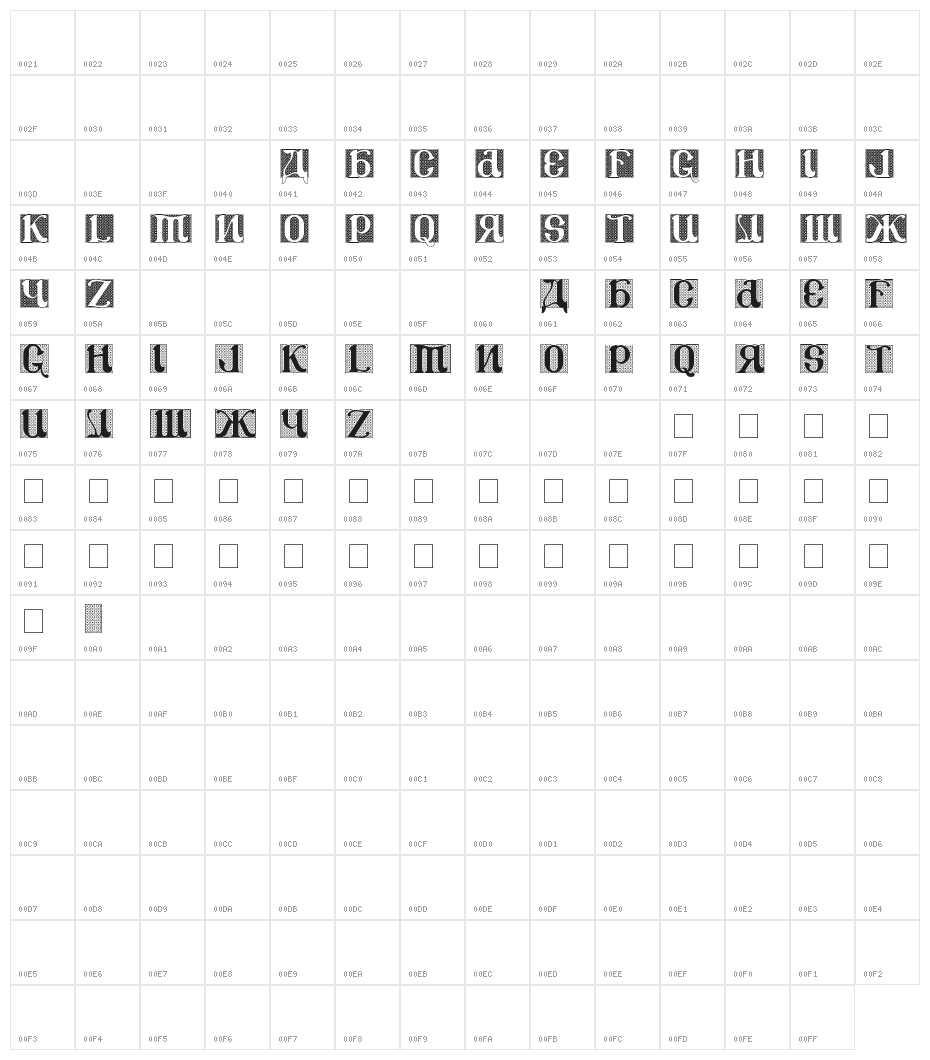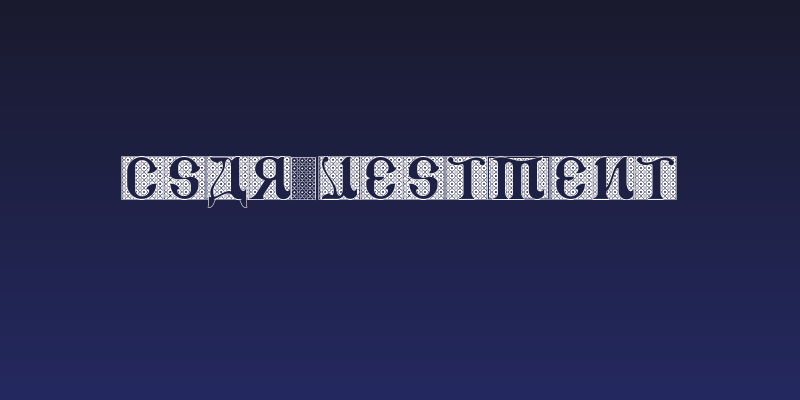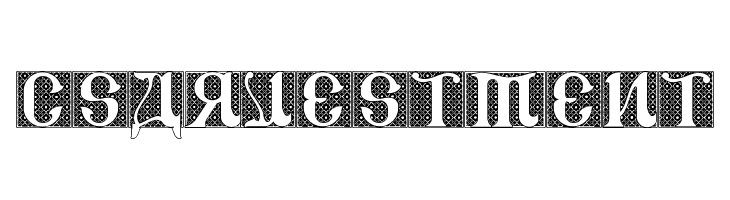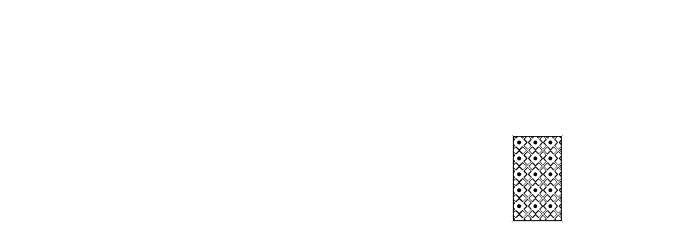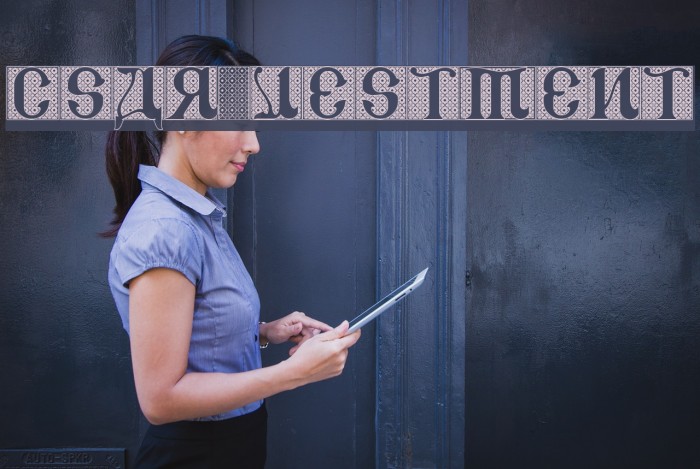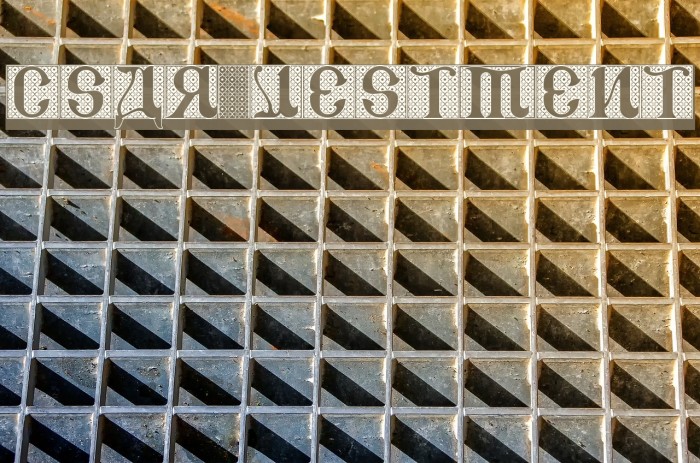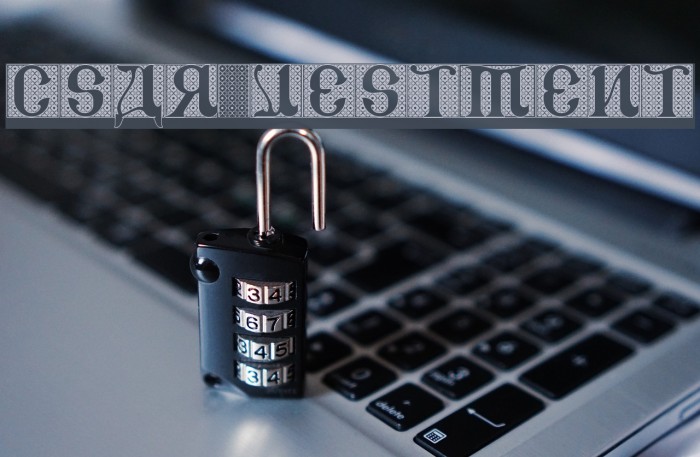
CSAR VESTMENT Font
✎ Thick
| Область применения | Headlines, Logos, Invitations |
| Рекомендуемые проекты | Ideal for use in invitations, posters, branding for luxury products, or any project that requires a touch of elegance and historical flair. |